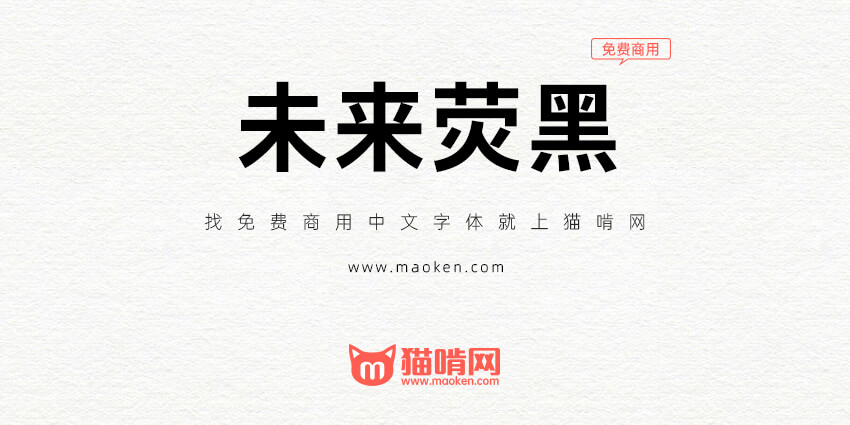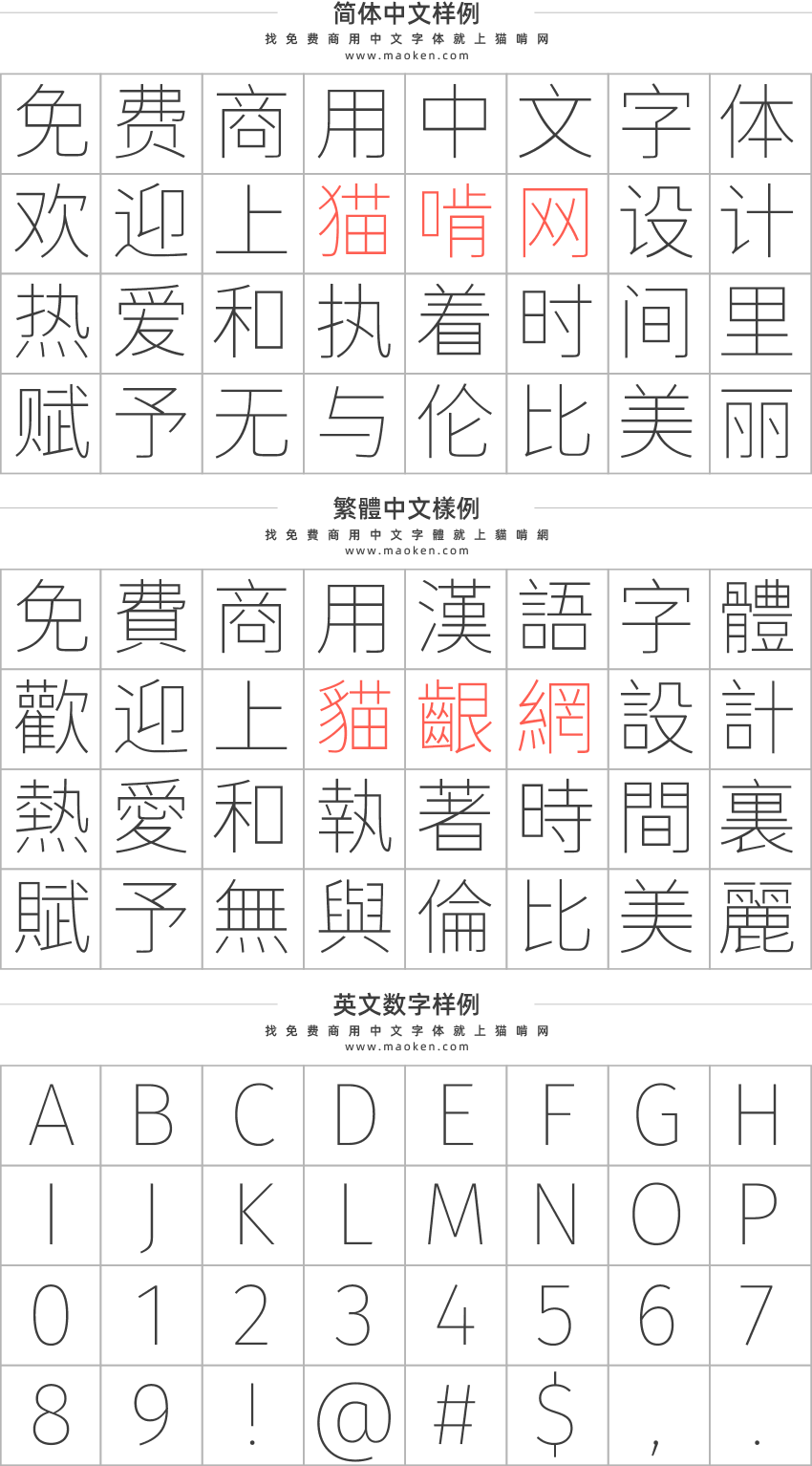
未来荧黑:拥有9字重更加简明现代的超大字体家族
字体作者:Celestial Phineas (中国大陆) 字体字重:9个
未来荧黑是一个基于思源黑体、Fira Sans和Raleway的开源字体项目,支持简体中文、繁体中文与日文;思源黑体的7字重被扩展为9字重,并提供了宽度系列,全家族共44款字体。
相比于思源黑体,未来荧黑的造型更加简明现代,版面效果清新轻快。未来荧黑的中宫与字面更加收敛,重心在字重之间经过了重新配置;笔画细节上处理得更加干练,简洁而平直化。您可以下载样张来预览未来荧黑的设计。
未来荧黑的实现介于参数化与轮廓滤镜,使用了图像处理算法对字形建模。字体的制作并没有借助字体设计软件,而是用一个Web实现的可视化调参工具来确定字体参数。
我们为未来荧黑开发了一个在线演示,同时它是未来荧黑修改字体参数的可视化交互环境。你可以在这里通过改变各种参数来修改文字样貌,导出的参数可用于字体构建。
Book字重专门为表格优化过欸,Excel换上舒适度瞬间提升
选了好几天字体,终于找到这一款,耐看,好辨认,细体很规整,粗体不那么呆板。那个调整字体的demo网页做得实在是太厉害了
这个字体有 bug,比如 “霞”、“葭”等字有误拔现象,“坝”字的笔画有问题,等等。
这款字体慎用,小写英文 fi 在一起时会组成一个不认识的字符!
• 亲,这是连字(Ligature)特性。可以好好查一下相关知识哦。
• opentype里可以关闭连字功能
這個字體後續可能會出韓文